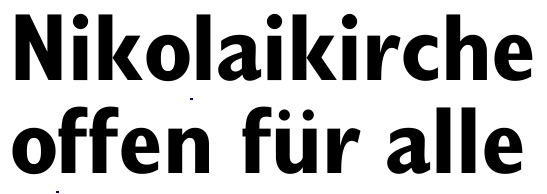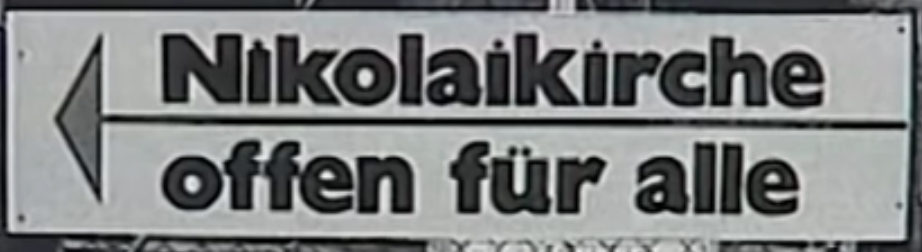
Schrift auf DDR-Schild in der Wendezeit
Ich habe heute ein Video gesehen, wie es damals mit der revolution los gegangen ist. Und hier ist mir eben eine Schrift aufgefallen, mit winzigen i- und Umlaut-Pünktchen.
Ich hatte auch gedacht, dass es etwas Gill_ish ist, und mir meine Verkehrs-GIL  aka TGL 12096.1  genauer betrachtet, und ich denke auch, das wäre wohl eine Heavy  dazu, wobei bei dieseer ja für die Verkehrsschilder-Anwendung die i und Ümlaut Pünkte deutlich vergrößert wurden, und hier dann entsprechend  extrem verkleinert wurden.
Das Bild kommt aus Leipzig aus der Zeit  kutz von dem "Republik-Jubiläum"  in der sie Staatsmacht schon heftigen Gegewind zu spüren bekam.
@catfontsMoin Peter, die i-Punkte wirken auf deinem Bild eher zentriert. Der erste wirkt so als würde da keine Luft mehr nach unten geben, als würde der i-Punkt mit dem Stamm darunter verschmelzen. erstes "i" wirkt auch so als würde sich der Stamm nach oben wölben. Das wird sicher an der Auflösung des Bildmaterials liegen., denn wenn man die beiden letzten i-Buchstaben betrachtet ist da wieder Luft und da wölbt sich auch nichts.
Ich bin kein Experte für Gill-Geschichte und ich bin mir nicht ganz sicher, auf welchem Schnitt dieses Schild basiert. Gegenüber der Kayo gibt es einige Unterschiede: das N ist breiter, das k ist gerade geformt, nicht gebogen. Auch das a sieht anders aus.
Die Gill bzw. eine kontinentale Variante von ihr war in der DDR recht gebräuchlich (z.B. auf Verkehrsschildern). Wäre sicher interessant, darüber Hintergründe zu kennen. – Dieses Schild vor der Nikolaikirche ist jedenfalls eine absolute Ikone der Zeit um 1989.